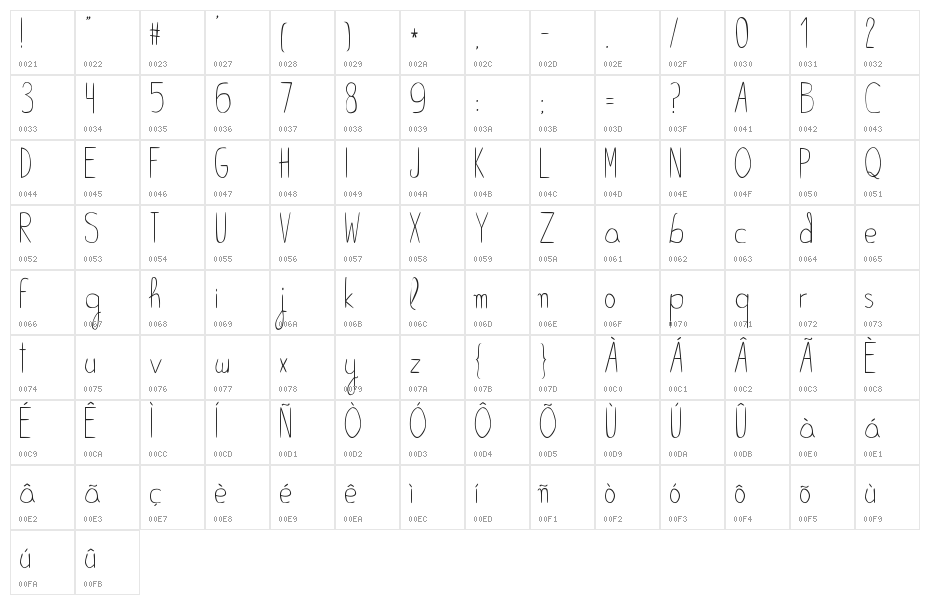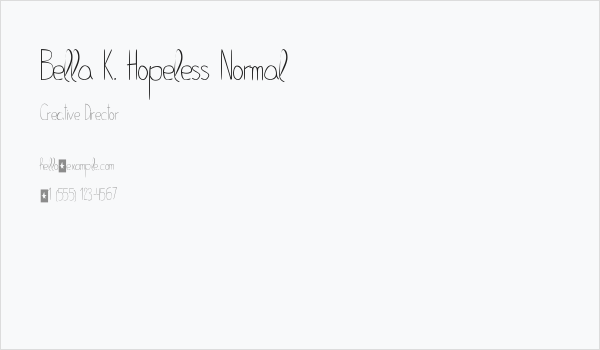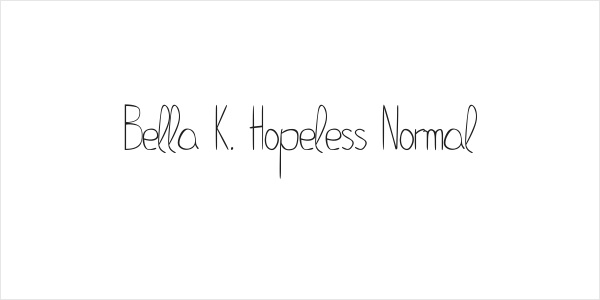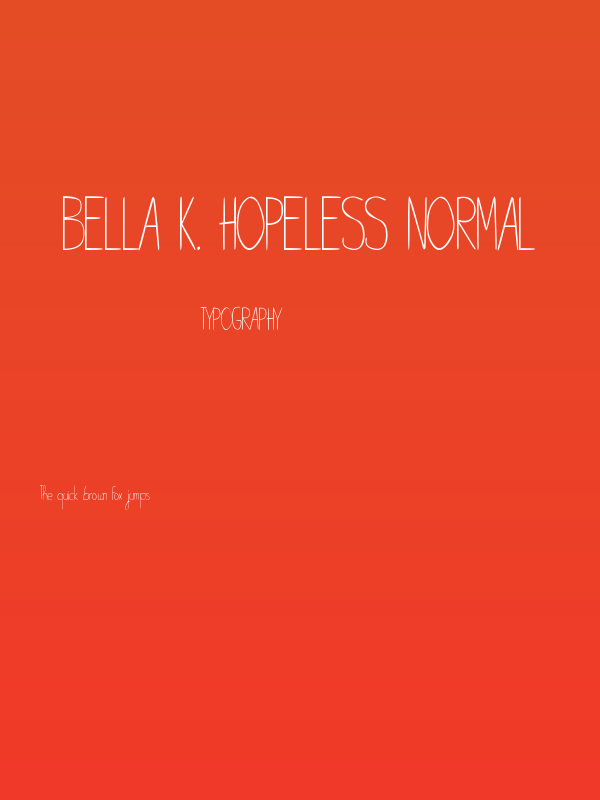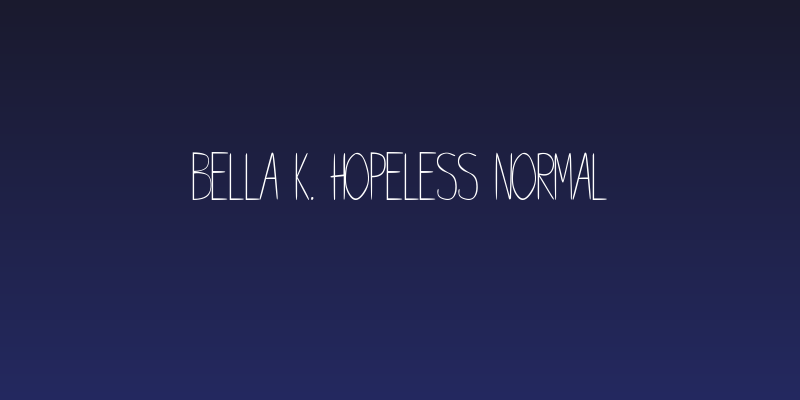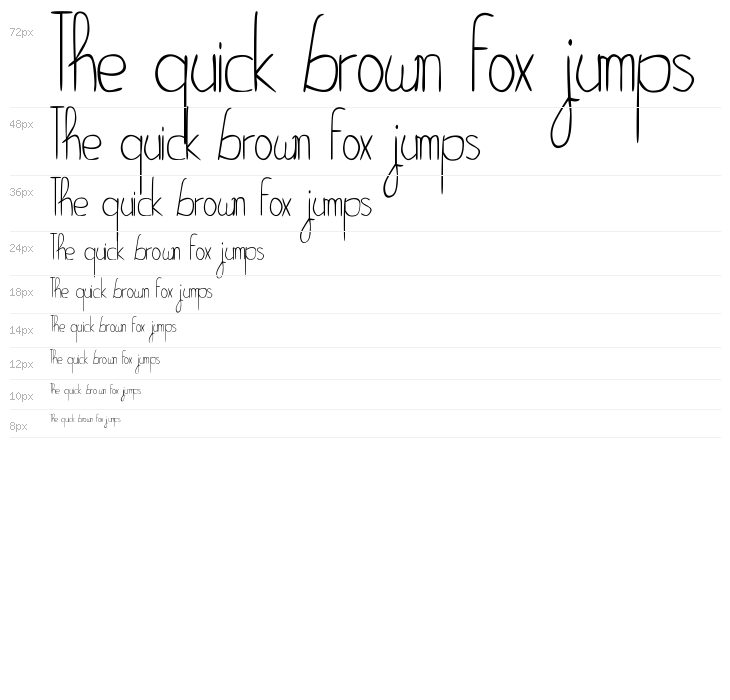
Bella K. Hopeless Normal Font
| Stile generale | Whimsical and Artistic |
| Caso d'uso | Headlines, Artistic Branding, Invitations |
| Progetti proposti | Ideal for creative projects such as invitations, greeting cards, and artistic branding. |